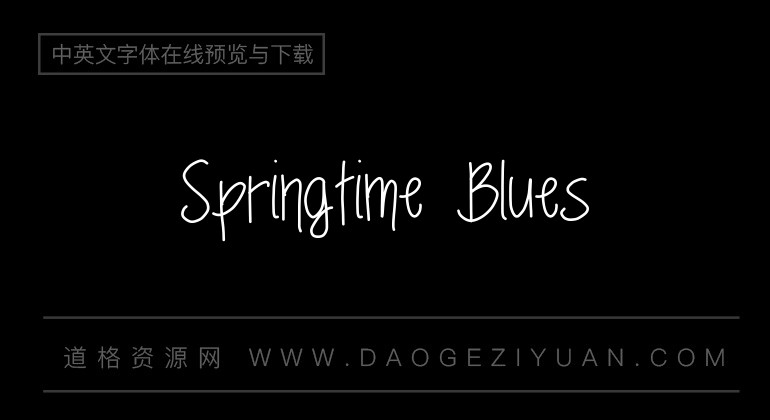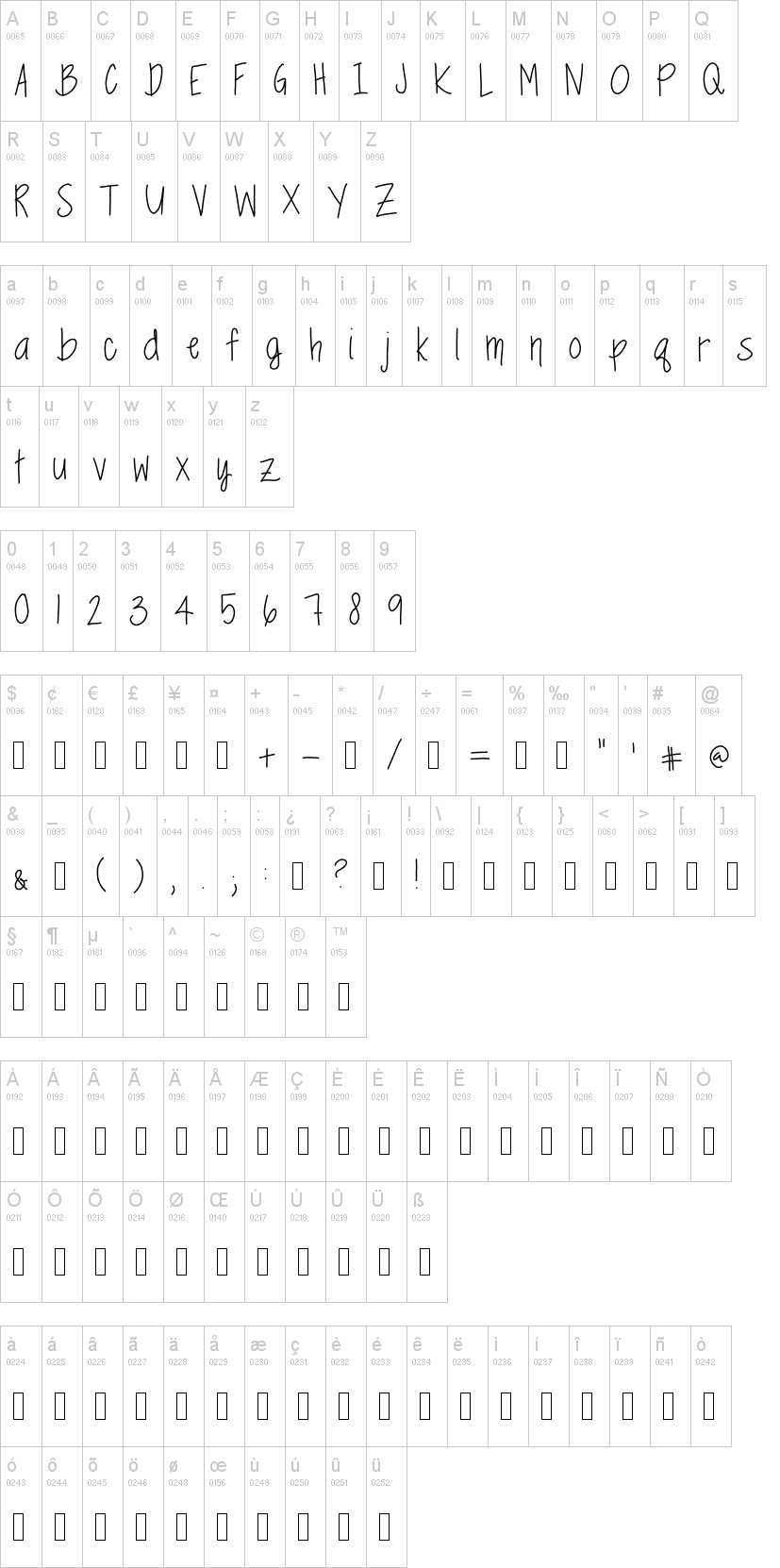
Springtime Blues
Springtime Blues 是一种手写风格的无衬线字体,由字体设计师 Arron Croasdell 创作。这种字体风格轻快活泼,适合用于卡片、海报、包装等设计中,能够为设计带来一种轻松、自然的氛围。 Springtime Blues 字体的特点是笔画不规则,形似手写,字母间距离较大,字母间有一定的交叉和重叠效果。该字体提供了多种不同样式的字母,包括大小写字母、数字和标点符号,支持英文、西班牙语等多种语言的编写。 Springtime Blues 字体的颜色可以根据设计师的需要进行自定义,可以使用单一颜色或渐变色来装饰文字。总之,Springtime Blues 字体适用于各种有关春季、自然、轻松和快乐的场景,并且能够为设计带来一种温馨、柔和的感觉。
Springtime Blues是一款非常不错的手写艺术字体,具有很好的视觉感,适合于文化类的宣传设计、商业类品牌的广告和产品包装设计以及个性化文字排版等较多场景。